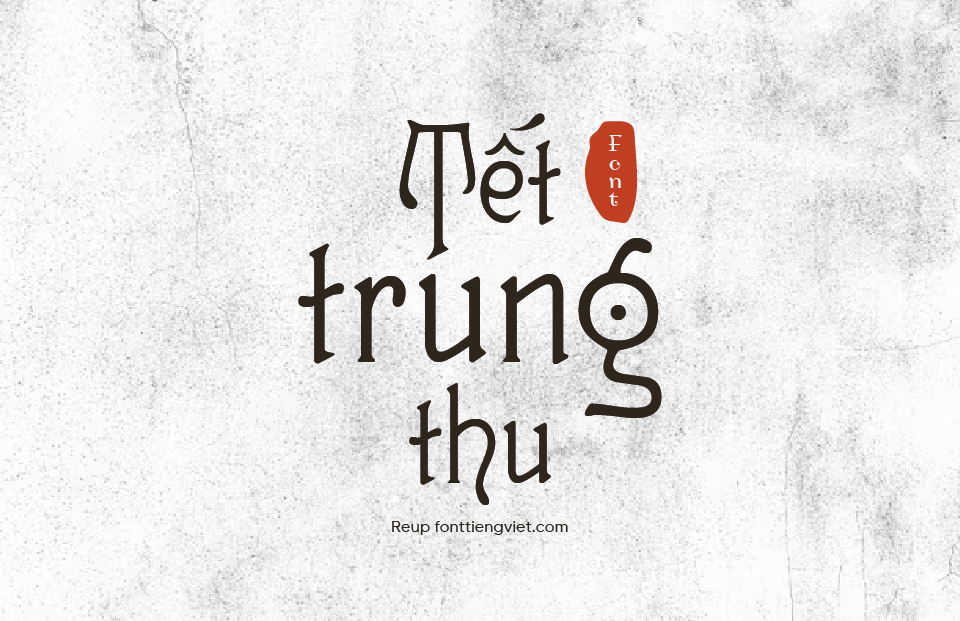
Font việt hóa LNTH Guttenberg MF – Font trung thu
Font việt hóa LNTH Guttenberg MF – Font trung thu cho thiết kế lễ hội truyền thống
Giới thiệu về Font việt hóa LNTH Guttenberg MF – Font trung thu
Trong các hoạt động giáo dục và văn hóa tại nhà trường, việc chuẩn bị tài liệu trực quan cho ngày rằm tháng Tám luôn cần sự tỉ mỉ. Bộ Font Miễn Phí chất lượng cao là công cụ đắc lực giúp thầy cô và học sinh sáng tạo. Đặc biệt, Font việt hóa LNTH Guttenberg MF – Font trung thu nổi bật với phong cách cổ điển, mang đậm nét hoài niệm và ấm cúng. Đây là lựa chọn hoàn hảo để tái hiện không gian lễ hội trăng rằm đầy ý nghĩa thông qua các biểu ngữ, thiệp mời hoặc tranh vẽ cổ động.
Đặc điểm nổi bật của bộ Font việt hóa LNTH Guttenberg MF – Font trung thu
Phong cách thiết kế và tính ứng dụng
Mẫu font này sở hữu những đường nét uốn lượn tinh tế, mô phỏng kiểu chữ in thủ công thời xưa. Font việt hóa LNTH Guttenberg MF – Font trung thu giúp các em học sinh dễ dàng tiếp cận với nghệ thuật chữ viết truyền thống. Độ tương phản giữa các nét thanh và nét đậm tạo nên sự hài hòa, giúp thông điệp trở nên rõ ràng nhưng vẫn giữ được vẻ đẹp nghệ thuật. Font được tối ưu hóa đầy đủ bảng mã tiếng Việt, đảm bảo không xảy ra lỗi hiển thị khi soạn thảo các đoạn văn bản dài.
Lý do nhà trường nên sử dụng bộ font này
Sử dụng Font việt hóa LNTH Guttenberg MF – Font trung thu trong các dự án học tập giúp rèn luyện tư duy thẩm mỹ cho học sinh. Khi thiết kế đèn ông sao hay trang trí bảng lớp, bộ font này mang lại cảm giác thân thuộc, gắn kết tình cảm gia đình và tình thầy trò. Sự linh hoạt của font cho phép áp dụng trên nhiều chất liệu từ giấy in đến màn hình trình chiếu một cách chuyên nghiệp.
Kết luận và trải nghiệm Font việt hóa LNTH Guttenberg MF – Font trung thu
Việc lựa chọn phông chữ phù hợp không chỉ làm đẹp văn bản mà còn truyền tải tinh thần cốt lõi của ngày Tết Thiếu nhi. Font Miễn Phí, Font Việt Hóa, Font việt hóa LNTH Guttenberg MF – Font trung thu chính là mảnh ghép còn thiếu để hoàn thiện các thiết kế mùa lễ hội. Hy vọng bộ font này sẽ mang đến niềm cảm hứng sáng tạo bất tận cho cộng đồng yêu thiết kế tại Việt Nam.